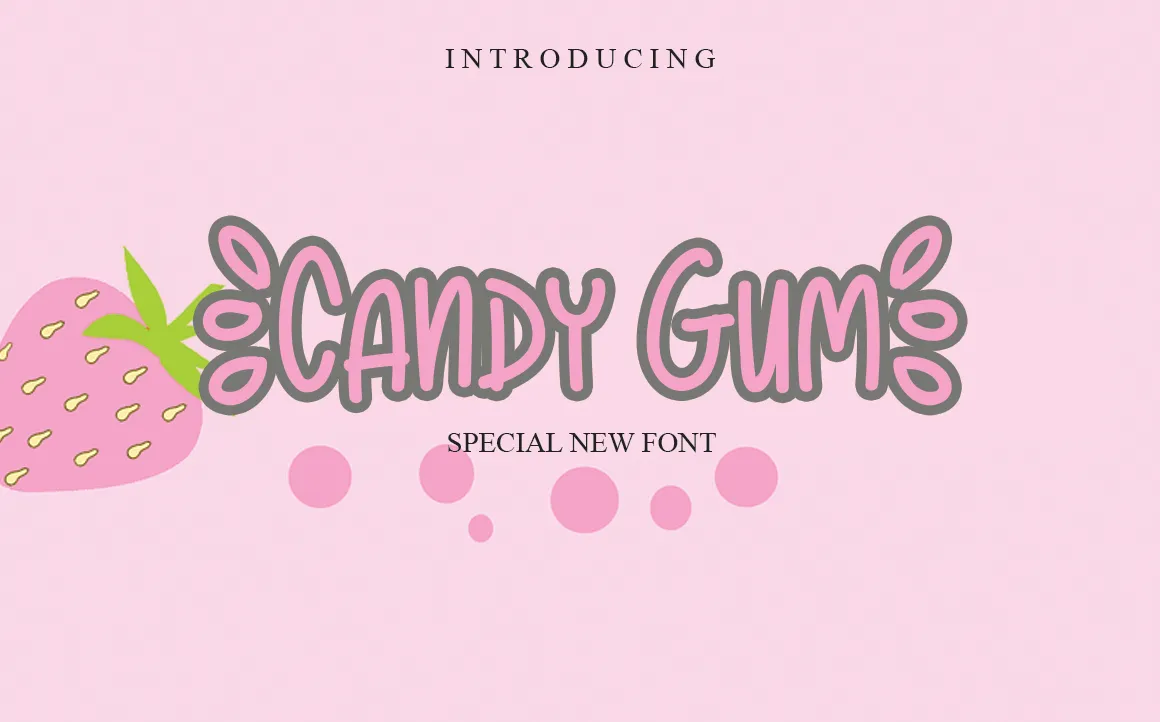
Esta fonte script é perfeitamente adaptada para projetos que exigem uma pitada de originalidade e criatividade. Ela se destaca pelo seu estilo descontraído, onde linhas finas e suaves se fundem com traços rústicos, criando um resultado visual encantador. Seja você um designer digital buscando adicionar um toque único em suas postagens de redes sociais, ou alguém que deseja incorporar elementos artesanalistas em seu próximo projeto DIY, a Candy Gum Script Font transformará seus ideias imaginativas em verdadeiros trabalhos de arte. Com uma aparência leve e deslizante, ela captura o espírito da escrita manuscrita, permitindo que qualquer criatividade seja expressa de maneira vívida e emocionante. Com sua versatilidade e qualidade superior, a Candy Gum Script Font se torna uma escolha ideal para quem busca personalizar suas criações digitais sem abrir mão do charme e da simplicidade característicos de um tipo à moda antiga.